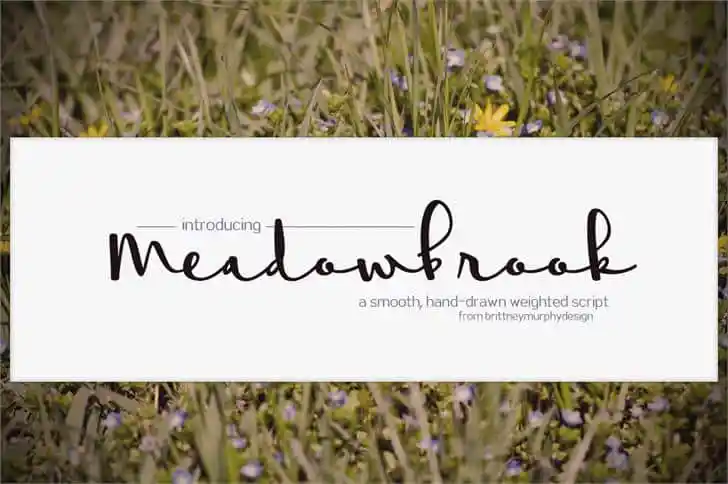
A Meadowbrook Font é uma mão-dura autêntica e elegante criada pelo designer Hamilton. Seu traçado suave e fluido permite que você personalize seu design sem perder a sofisticação, tornando-a uma escolha perfeita para qualquer projeto de escrita livre ou fontes manuscritas. A Meadowbrook é não apenas uma fonte bonita, mas também um recurso versátil para designers de todos os níveis. Seja você trabalhando em cartazes promocionais, criação de aplicativos móveis ou design editorial, a Meadowbrook oferece as características perfeitas para dar seu projeto um toque único e profissional. Para adquirir uma licença confiável desta fonte, visite o site do designer: https://brittneymurphydesign.com/downloads/meadowbrook/.